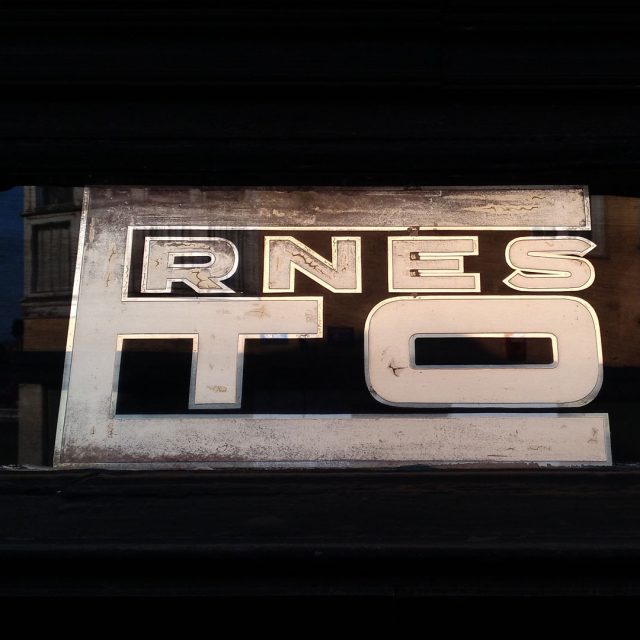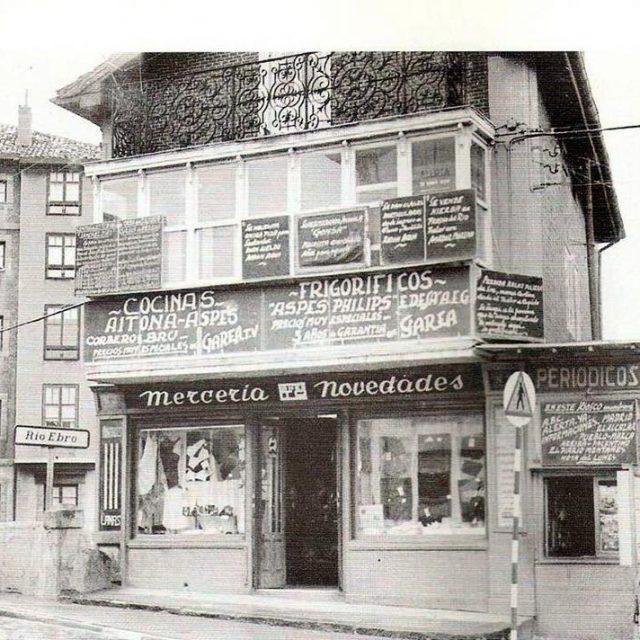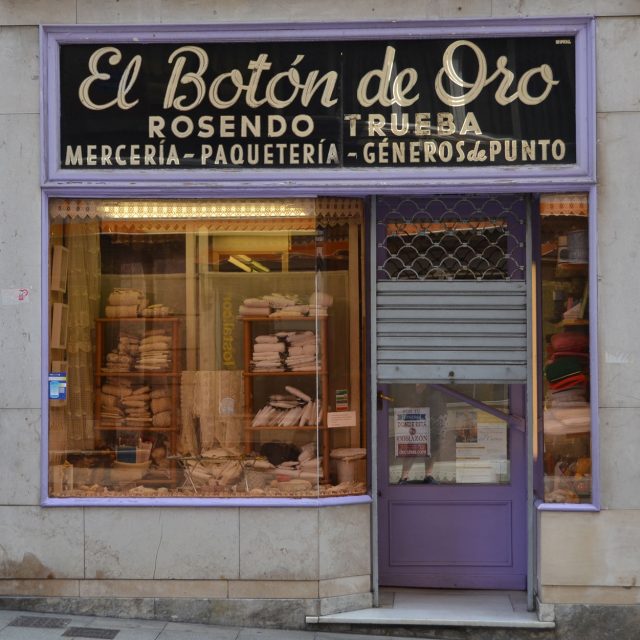
¿quién es Noval? Primer enlace Reinosa – Santander
Dando un paseo por Reinosa, no se puede dejar de mirar para arriba donde hay todo un universo de tipografías e Historias que se conservan y que lo cierto es que Reinosa merece un Safari Tipográfico propio, que nos gustaría dar a conocer más a fondo.
Por cosas de la vida, admirando uno de esos rótulos, algo te resulta familiar. Puede ser el estilo y la técnica, quizás la letra, pero es la firma quien nos da la voz de alarma: NOVAL. No tardamos en recordar que en Santander hay un rótulo que está también firmado por el mismo. Revisando la web, confirmamos la sospecha de que se trata del rótulo de El Botón de Oro (1954)
El rótulo en cuestión de Reinosa es el de la Mercería Ernesto Novedades (Avda. Puente Carlos III). No tenemos datos concretos, pero gracias a esta linea abierta podemos intuir que estamos hablando de los años 50. En técnica de ácido, vemos una tipo script y lo más curioso y que da un toque moderno es la composición geométrica de Ernesto. Esto recuerda también a la palabra confitería de Máximo Gómez en el Paseo Pereda de Santander.
En Santatipo no sólo queremos rescatar letras. También queremos rescatar del olvido el oficio y al artesano que hay detrás de cada letras y creación, aunque en este sentido ya hay gente que lo vuelve a poner en valor. Y este es un buen punto de inflexión para investigar sobre quien era NOVAL y si hay algún rótulo más en Cantabria con su firma. Poco a poco empezaremos a tirar del hilo, pero de momento podemos ir disfrutando con cada rótulo y cada letras hecha. Son elementos únicos hechos a mano y que si alguna vez desaparecen, también desaparece parte de la historia de la producción creativa de Cantabria.
Detalle de la composición geométrica del nombre “Ernesto”
Detalle de la Firma NOVAL. Arriba el Botón de Oro. Abajo, Mercería Ernesto
Foto en la que se ve que el edificio servía como soporte para distintos anuncios y que era conocido como el “Tablón de Chirigata”. Historia y foto compartida por Jesús Allende Valcuende (Porende Estudio Gráfico).
“El Botón de Oro” el otro rótulo de Noval conocido, de momento, en Santander. La firma se puede apreciar en el lado superior derecho.